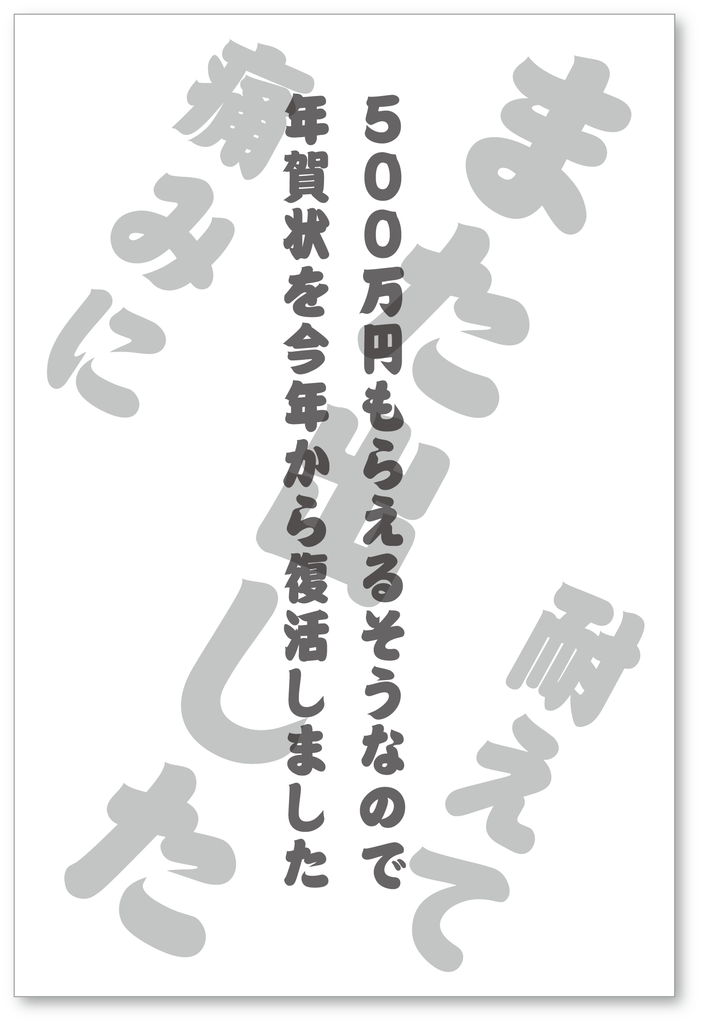
気力・体力・財力の限界…、全ての年賀状にギブアップ宣言!
長らく日本の年始の文化だった年賀状だが年々、減少そており、死滅しそうな気配だ。
年始の挨拶として普段なかなか会えなくても繋がっていたい人に感謝を込めたり、「まだ生きてるよ」という生存確認のメッセージであったり、お正月の風物詩としてこれまで日本人の交流を支えてきた年賀状には「買う・書く・送る」という3つの手間を要する。
しかし、携帯電話の所有が当たり前となり、はたまたスマートフォンの所有率も格段に上がった昨今、メールでの年始の挨拶はもとより、LINEなどSNSで、そうした3手間を必要としない気軽に行える年始の挨拶が浸透していく中、いつしか年賀状という文化は時代にそぐわないものになりつつある。
さらに追い打ちをかけるように「終活年賀状」という考え方も浸透し出しているようだ。
「終活年賀状」
「終活年賀状」とは、交友関係を整理する「終活」の一環として来年からの年賀状のやりとりの辞退を宣言する年賀状を送ることで、年賀状仕舞いとも呼ばれているようだ。
この「終活年賀状」は、いわゆる年賀状の「買う・書く・送る」といった3重苦で「気力・体力・財力」を消耗する行動に対するギブアップ宣言ともいえる。
そして、この「終活年賀状」を行う人間は何も高齢者だけに限った事ではない。いざなぎ景気を超えたらしいが何も実感が沸かない景気回復や待ち受ける増税という世知辛い日本社会を生きる全ての人間が行ってしまっても不思議ではない行動だといえる。現に私も年賀状を送る事を諦め、ギブアップしてしまった終活年賀人間の1人である。多少の気まずさはあるものの、喉元過ぎればなんとやら、正月過ぎれば出勤だ、と日々の暮らしの中で、今を生きるだけで一杯いっぱいとなり、その気まずさは薄れていく次第。
終活年賀状を「体力の限界」という台詞に持ってこいの「相撲体」で表現
「相撲体」は、江戸時代に使用された図案文字である江戸文字の一つ「相撲文字」をデジタル化した書体。隙間が少なく直線的なのが特徴。「相撲文字」だけに大横綱である千代の富士が引退した際の名言「体力の限界」にもピッタリで、「気力・体力・財力」の限界を宣言する終活年賀状にも最適な気がする。
終活年賀状を伝える、怯える心理を表現したいなら「ホラー」で表現
「ホラー」は、怯えや恐怖といった強烈な体験をイメージしてデザインされた書体。 終活年賀状を相手に告げる際、相手を怒らせないか怯えを表現するのに適している気がする。
年賀状を送り続けた事で、心がひび割れかけている事をアピールするなら「ひびゴシック体」で表現
「ひびゴシック体」は、極太のゴシック体にひびが入ったようなデザインのフォント。 すでに心にはひびが入ってる状態であり、このまま年賀状を出し続けることで、いつ粉々になってもおかしくない状態、どうか察してくださいという事を告げるのに適していそうだ。
年賀状をとにかく「限界」だということを伝える「限界明朝」で表現
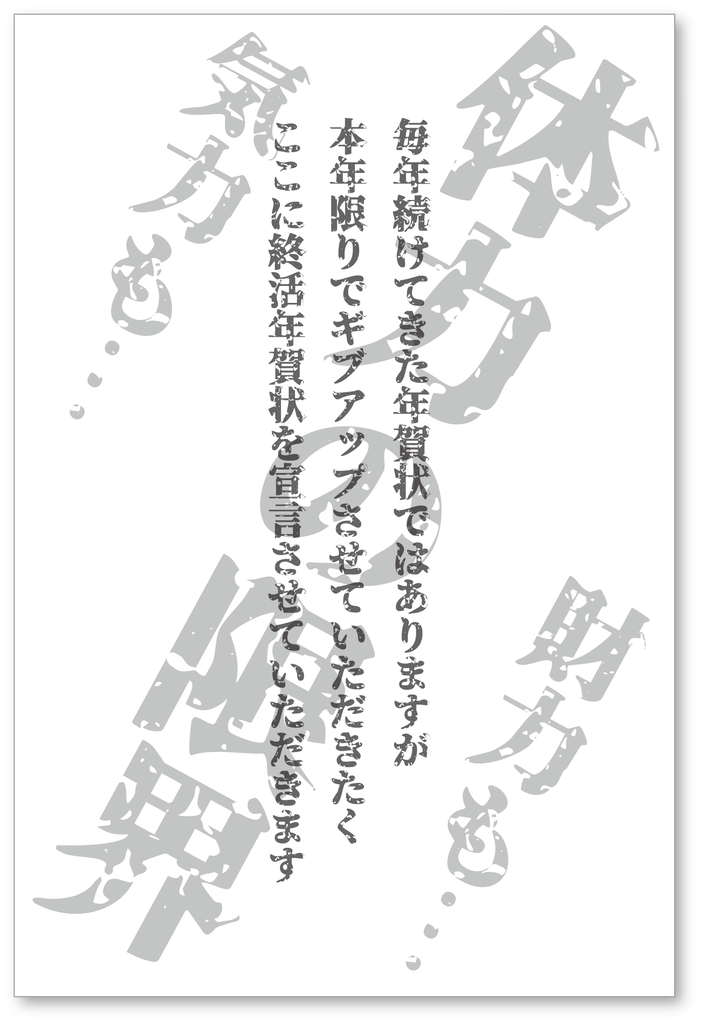
「源界明朝」は、オープンソースのフォント「源ノ明朝」の派生フォントで破壊されて限界ギリギリ読める仕上がりとなっているフリーフォント。年賀状を出すことについて「シンプルに限界です。」という事を告げるのに適している。
年賀状が復活する方法を本気出して考えてみた
言葉は悪いが、年賀状を送るという「買う・書く・送る」という3手間を経ても得るのは僅かばかりの「心」だ。
もちろん、こちらから送った所で相手からは送ってもらえる保証もない。
「私が年賀状を送りたいだけだから見返りなんて気にしないさ!」という強い心を持った人間ならば良いが、人間誰もが無償の奉仕を良しとはせず、見返りを求めない清貧とも呼べる「心」のみでは生きてはいけない私のような人間もいるのだ。
おまけに年賀状には、1月1日に届くように書かなければいけない…という無言の圧、超絶なプレッシャーとなる締め切りまで備えているから始末におけない。
もう一度言うが、こうした手間に対して…、見返りは余りに少ないッ…。
否!年賀状「お年玉賞品」があるじゃないかッ!…という反論も有るかもしれないが、年賀状「お年玉賞品」がもらえるのは、送られた側なのである。
これではいけない…!
これでは出せない…!
もう年賀状なんて出さないなんて言わないよ、絶対♪なんて言えない…!
このままでは年賀状に未来などない。
出したいだけ出せばいいさ、続けたい人だけ続ければいいさ…という考え方では、分母は減る一方、やがて年賀状は死滅してしまうだろう…。
それでよいのか日本郵便? お年玉賞品を少しばかり増やしただけでは、先細るのみ。SMAP亡き今、日本のアイドルのトップに君臨する嵐を起用し、復活への闘志を燃やしているであろう日本郵便へ届けと、私は年賀状が復活する方法を本気出して考えてみたのだった。
日本郵便株式会社は郵政民営化し、現在では上場会社である。年賀状のCMに嵐を起用する資金もある。
じゃったら、いけるじゃろう、1,000万くらい!
年賀状を廃れさせない為に、年賀状お年玉賞品の一等に1,000万くらいいけるじゃろう!
そこで、私は正月に届く初夢として2020年から年賀状お年玉賞品の一等に送った500万円、届いた500万円を提案したい。
そしてこのアイデアが採用されたらアイデア料を私におくれ!
【日本郵便くんへ届け!】年賀状を廃れさせない為に年賀状お年玉賞品の一等は正月に届く初夢として2020年から送った500万円、届いた500万円が貰えるWinWinな年賀状を提案したい
フフ…へただなあ、日本郵便くん。へたっぴさ…!
年賀状の復活のさせ方がへた…。
我々が本当に欲しいのは…百万以上…
それも届いた側だけでなく…送った側ももらえるようにして…
財布をホックホクにしてさ…これでこそWinWin…だろ…?
フフ…。だけど…それはあまりに値が張るから…
30万の…しょぼい金額でごまかそうって言うんだ…。
日本郵便くん、ダメなんだよ…!
そういうのが実にダメ…!
せっかく賞金を出すんならスカッと出した方がいい…
その妥協は傷ましすぎる…!
そんな金額を出してもうまくいかないぞ…!
嘘じゃない。かえって出す気が起きない…!
食えなかった焼き鳥がチラついてさ…
全然スッキリしない…!
心の毒は残ったままだ、我々への賞金の出し方としちゃ最低さ…!
日本郵便くん…賞金ってやつはさ…
小出しはダメなんだ…!
出す時はきっちり出した方がいい…!
それでこそ次の年の年賀状を出す励みになるってもんさ…!
違うかい…?
2019年のお年玉商品の一等は、前年の10万円から金額が3倍にアップして現金30万円かもしくは同額相当のプレミアム賞品がもらえるようになった。
プレミアム賞品は、ふわっとしているが「憧れの実現」や「最新技術の体感」をコンセプトに、旅行や特別な体験型プランなどお年玉付年賀葉書ならではの豪華賞品が用意されている。
当選確率は100万本に1本2,412本。
2等は、ふるさと小包などで1万本に1本の割合で241,281本。
3等は、62円切手と82円切手が入った切手シート「お年玉切手シート」。おめでたい招き猫のデザインで、当せん割合が前年の100本に2本からアップし、100本に3本72,384,360本。
また、東京2020大会[寄附金付]年賀葉書(無地(インクジェット紙)・絵入り・特殊印刷)や、2019年用年賀葉書の無地・無地(くぼみ入り)・無地(インクジェット紙)・無地(インクジェット写真用)を対象に旅費(交通費、宿泊費)に充当いただける旅行券付きで東京2020オリンピックへペアで招待される「東京 2020 大会応援賞 」も当たるようだ。
1等30万円…。
さっきも書いたが、これではいけない。
思い切りにかけた賞金で、しみったれている感じも受ける。
民営化・上場・嵐のCM起用という潤沢な資金力があるであろう日本郵便にはもう少し頑張っていただき、1等は1,000万円(送った側500万円/送られた側500万円)、2等は100万(送った側50万円/送られた側50万円)、3等は10万円(送った側5万円/送られた側5万円)、4等は1万円(送った側5,000円/送られた側5,000円)、5等は切手シート1,000円(送った側500円/送られた側500円)でお願いしたい。
消費税増税など2019年も何の希望も無さそうな中、正月に届く初夢として庶民にもそれくらい夢を与えていただければ、年賀状を貰う喜び、出す喜びもあるというもの。
でなければ年々、年賀状という文化は無くなりはしないが、廃れていくのみと思える。
今回の提案は以前、「22018年12月のmojiru【もじをもじる】解析書いた提案から少し改良させてもらっている。
年賀状を送られた側だけでなく、送った側にも利点があるように。
送った側も送られた側も嬉しいWinWinな年賀状お年玉賞品の仕組み
1. 年賀状を購入する時、その年賀状のお年玉賞品の番号が書かれた別紙も発行される仕組みに改変。
2. 年賀状購入者側は、番号が書かれたその別紙が貰える。